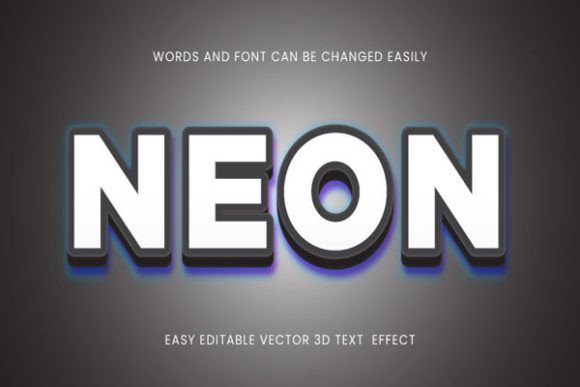
Neon 3d Editable Text Effect Font
Att hitta rätt designelement kan vara utmanande, men Neon 3d Editable Text Effect Font erbjuder en exceptionell samling som omedelbart lyfter ditt arbete.
Tillverkad med precision, ger Neon 3d Editable Text Effect Font rena vektorer, smidig typografi och en kommersiell licens för sinnesfrid.
Oavsett om du skapar POD-produkter (Print on Demand), bröllopsinbjudningar eller grafik för sociala medier, är Neon 3d Editable Text Effect Font ett perfekt val.